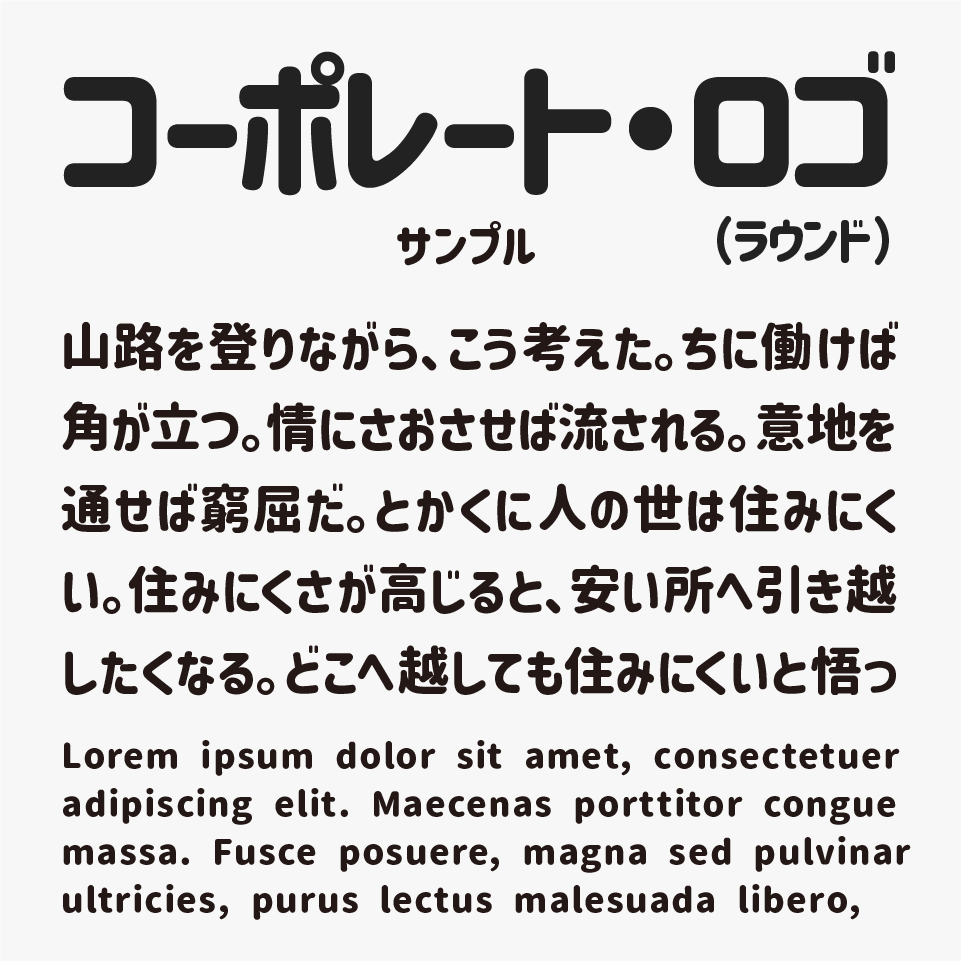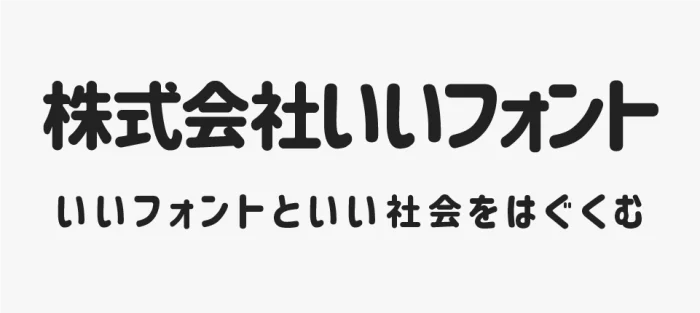
コーポレート・ロゴ(ラウンド)
コーポレート・ロゴ(ラウンド)フォントとは、「コーポレート・ロゴ」に角丸(ラウンド)加工を施した角丸ゴシック体フォントです。
角丸デザインでありながら、可愛らしくなりすぎず、かといって固すぎる印象にもならない絶妙なバランスがとてもステキなフォントです。
現代的でモダンな雰囲気やシンプルさはそのままに、やわらかく優しい印象がプラスされており、親しみやすさのあるデザインに仕上がっています。
ロゴデザインだけではなく、バナーデザインや資料作成など太さもあるので目立ちたい場面での見出しにも向いています。